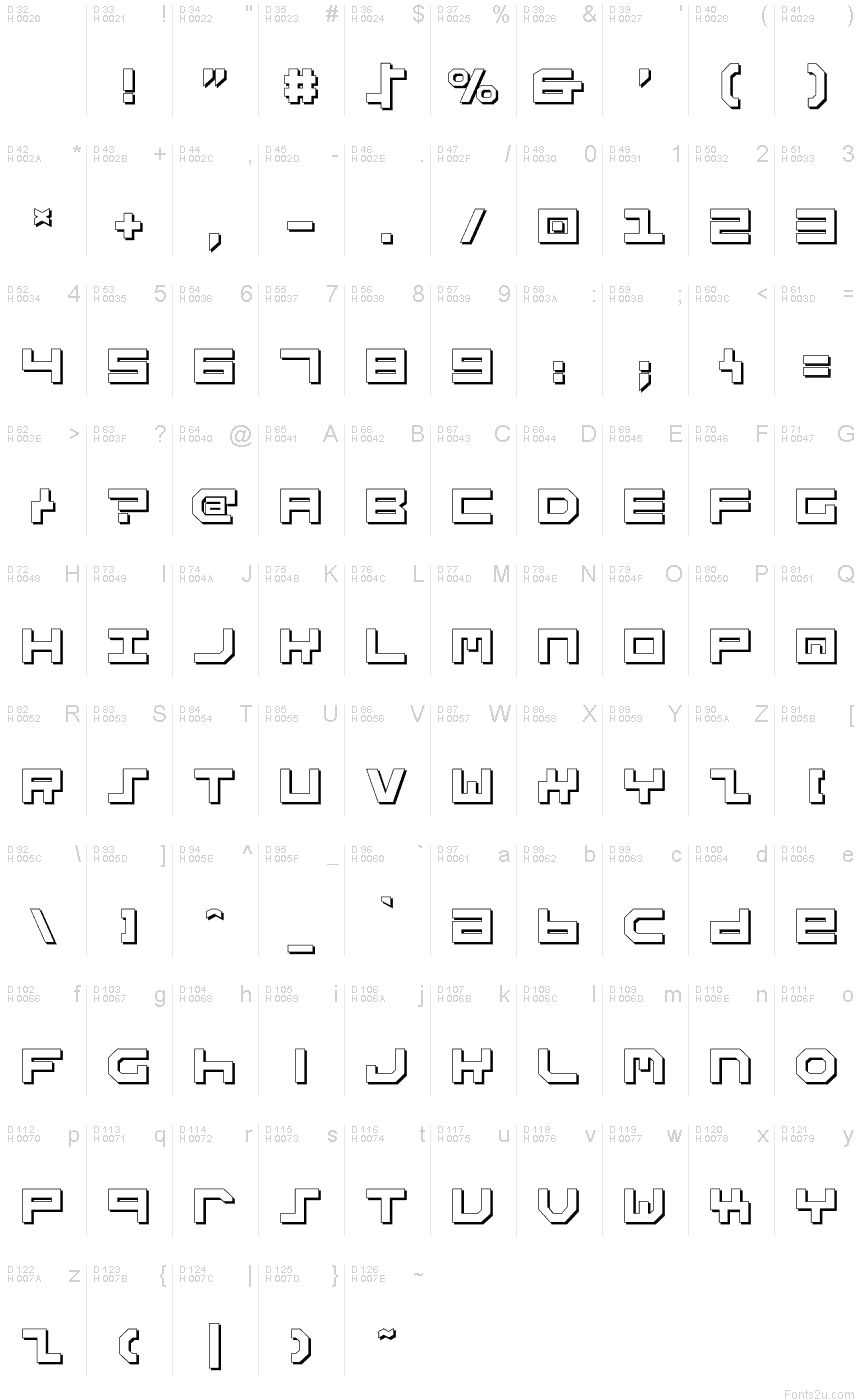
Stuntman Shadow من Iconian Font هو خط عرض (display font) مجاني بأسلوب تقني (techno)، يتميز بحروف ضخمة تحاكي عصر ألعاب الآركيد مع تأثير ظل مدمج. تبدو الأحرف الكبيرة وكأنها مقصوصة من البلاستيك الصلب أو المعدن، حيث تمنح الأشكال المربعة والزوايا المقطوعة الخط طاقة حيوية تشبه عناوين الألعاب، دون الانجراف إلى كليشيهات الخيال العلمي.
يتناسب هذا الخط بشكل طبيعي مع عناوين الملصقات، وتصميمات الألعاب الكلاسيكية (Retro)، وأغلفة القصص المصورة، ومنشورات الفعاليات، وبطاقات العناوين حيث تحتاج الكلمات القصيرة إلى لمسة ميكانيكية جريئة. ولأنه خط مجاني، فإنه يعمل بشكل رائع أيضًا للشعارات والأحرف المتداخلة (monograms)، حيث يضيف تأثير الظل بعدًا ووضوحًا حتى لأبسط الأحرف.